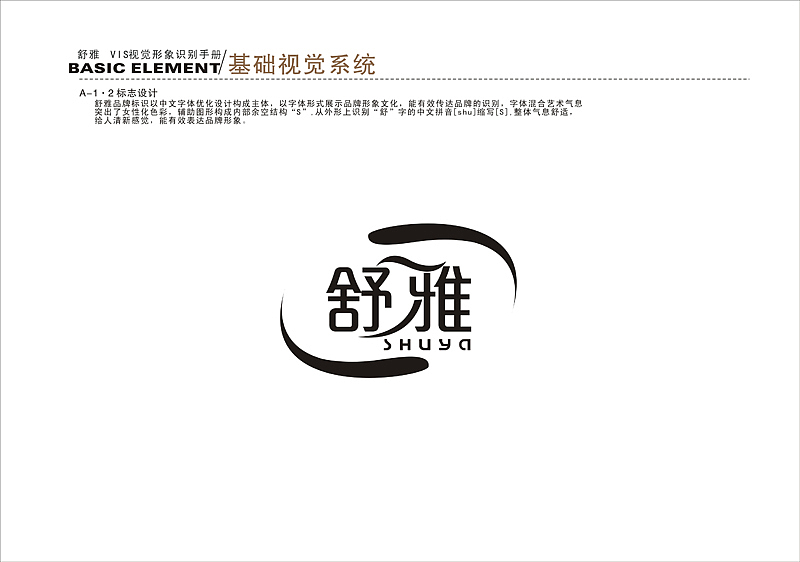
舒雅品牌logo设计字体设计(品牌logo正在受理中)
上班的时候给姐代理品牌设计的一个品牌logo,主要围绕字体构成!突出主体,但是用流线型气息构制标志,字体舒服,笔画简介比较符合品牌行业!花时间用手稿去完成的,还请大家给点意见!(品牌logo正在受理中,带请大家不要模范奥!)否则出现两个相似的就不好了!哈哈....